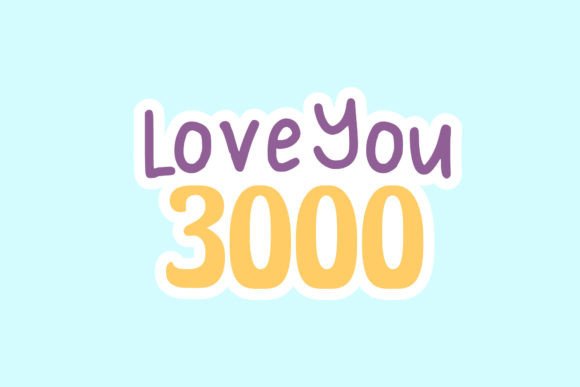
Valentine Typography Love You 3000
Encontrar los elementos de diseño adecuados puede ser un desafío, pero Valentine Typography Love You 3000 ofrece una colección excepcional que eleva tu trabajo al instante.
Elaborado con precisión, Valentine Typography Love You 3000 proporciona vectores limpios, tipografía suave y una licencia comercial para tu tranquilidad.